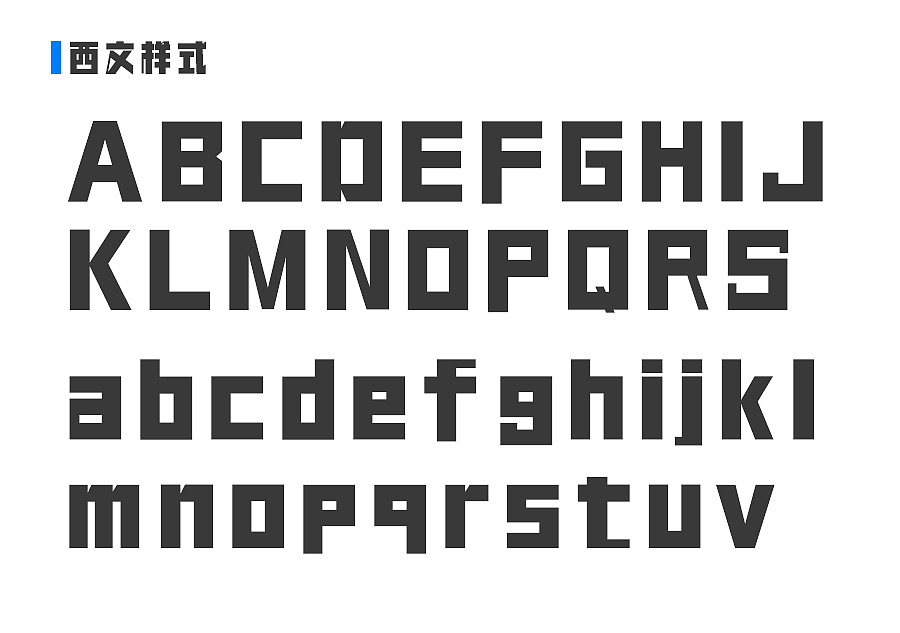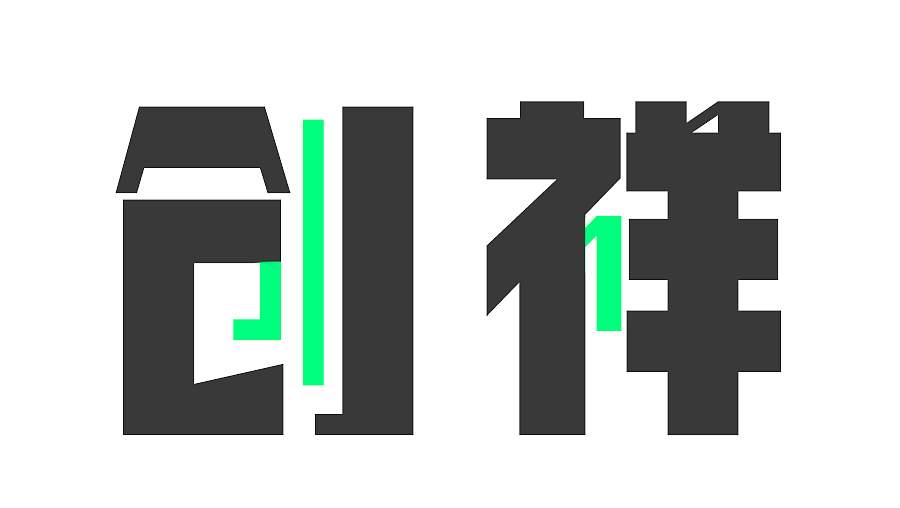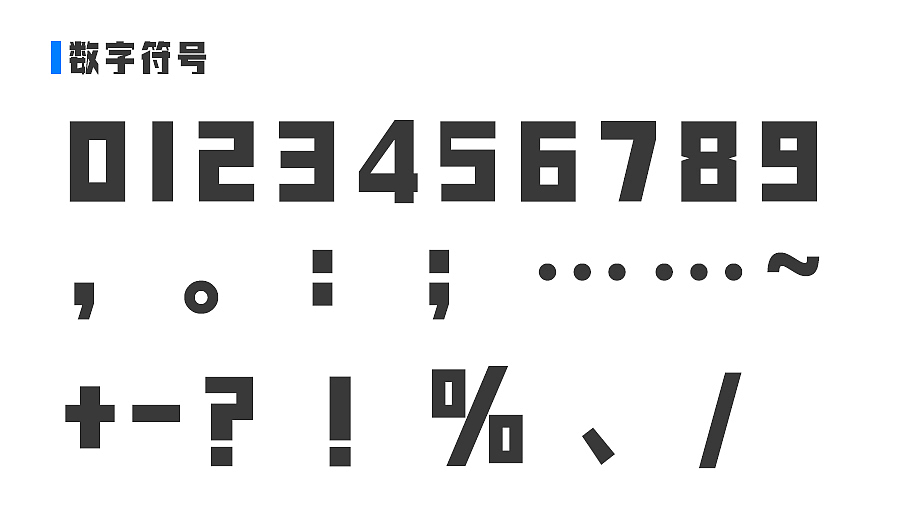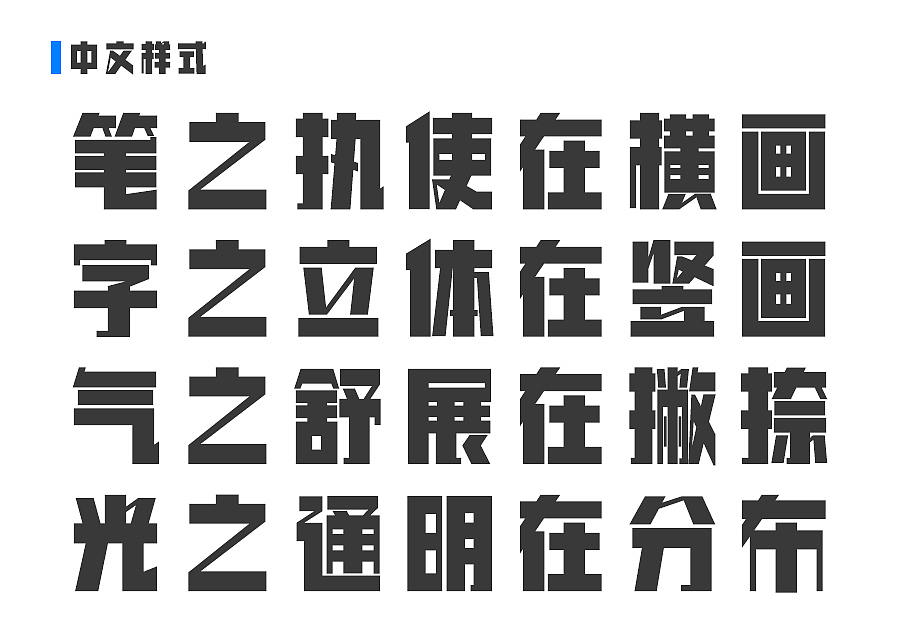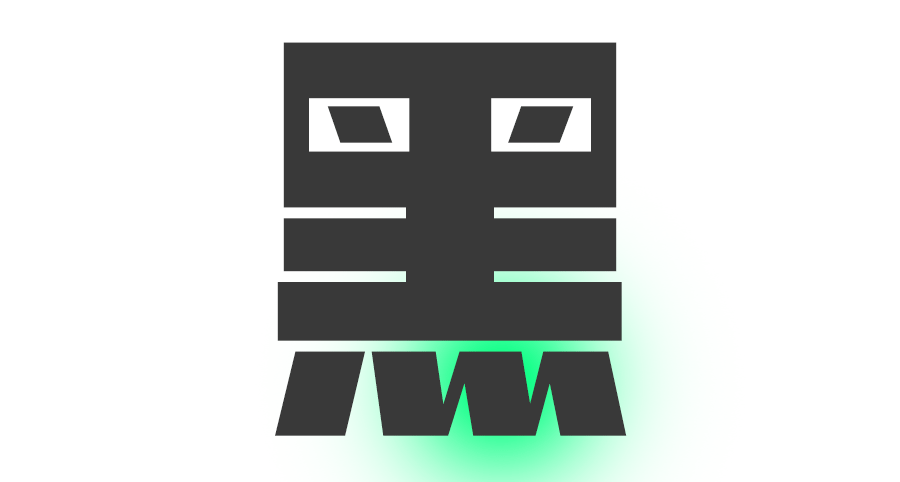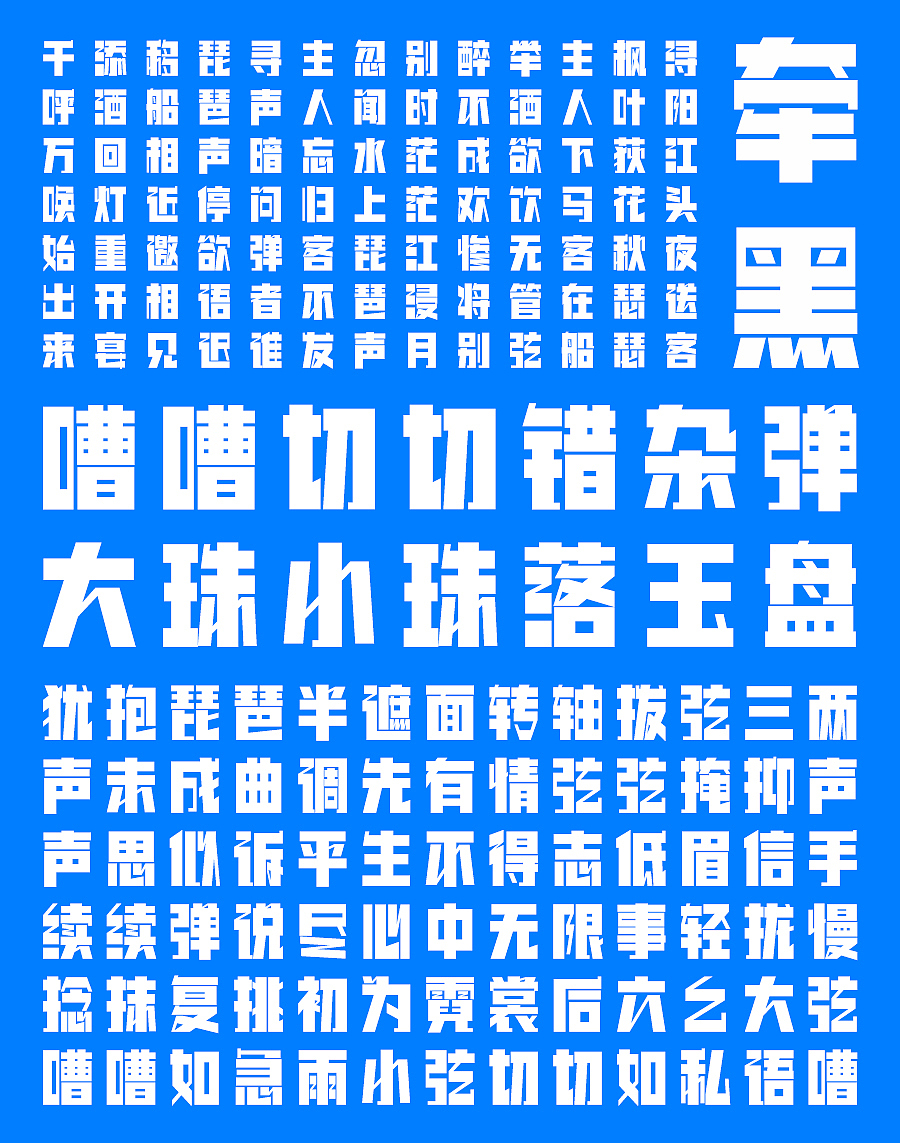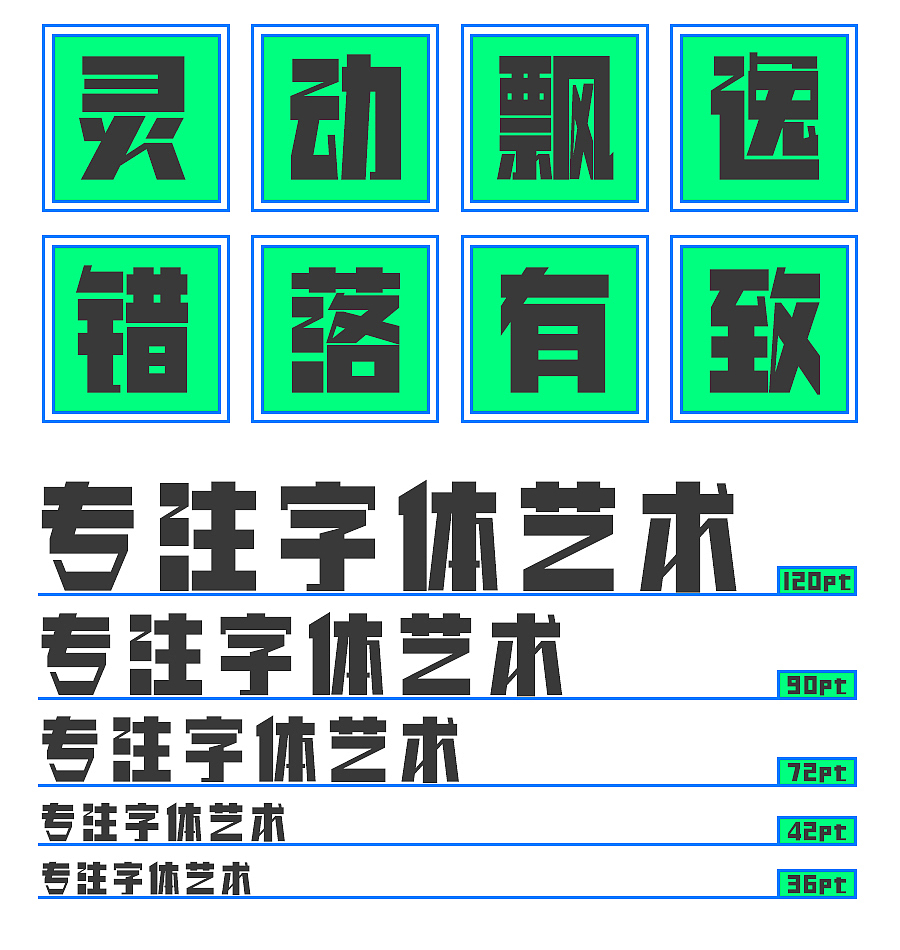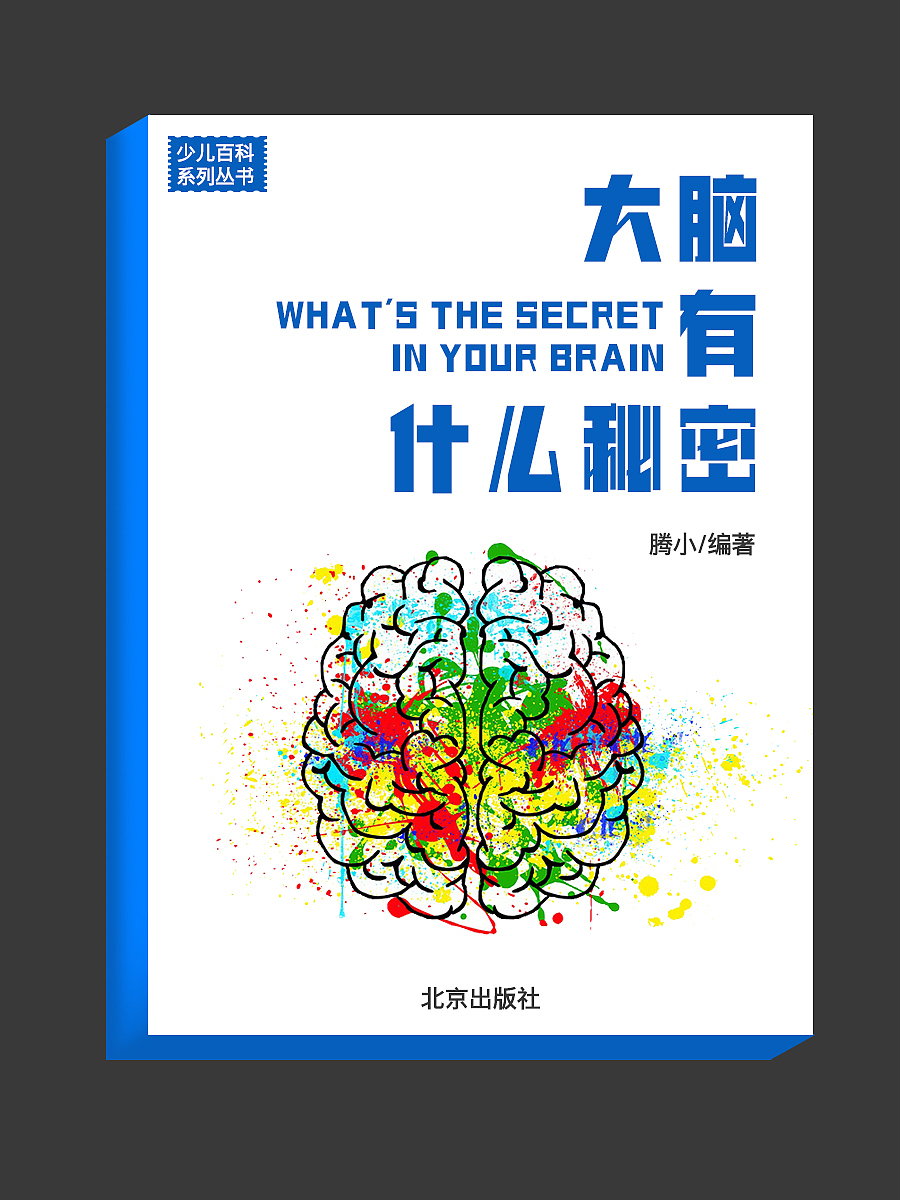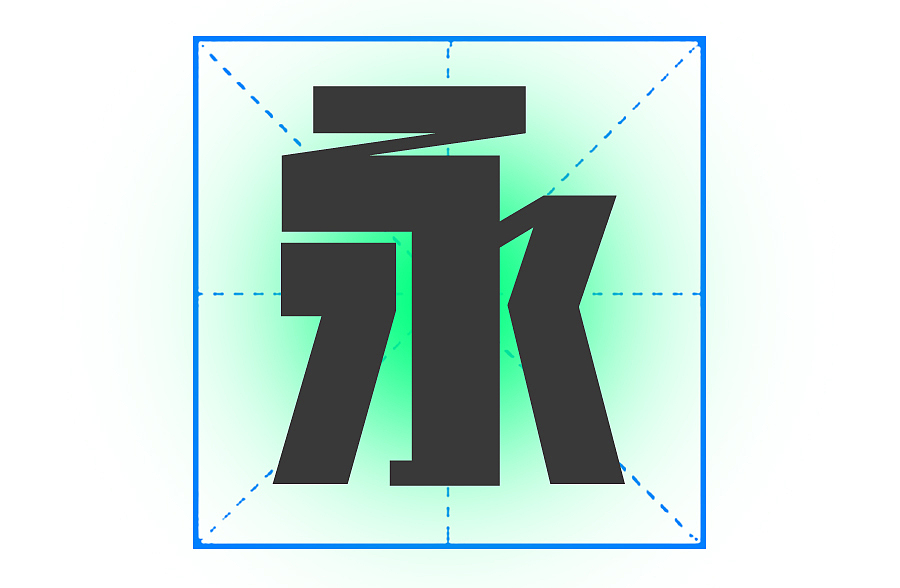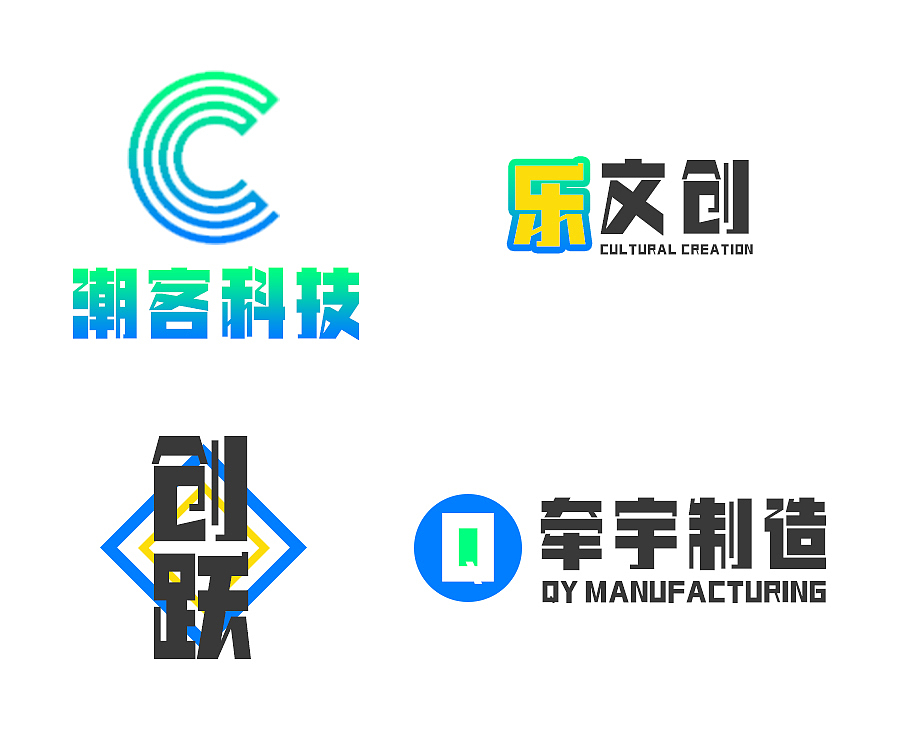
腾祥牵黑是腾祥公司自主精心设计开发的美术字体。牵黑体为黑体字形,其结构长方笔画粗壮醒目,其中细笔画穿插其中打破黑体字的沉闷,笔画粗细搭配协调,设计凝练巧妙,在不影响阅读的前提下牵黑体中特别设计了连笔笔画处理,使黑体字看起来灵动有手写感。整幅字给人以清朗醒目、别致新颖之感。设计师以独具匠心的设计手法诠释出牵黑体的别样风格。
*同一个部件搭配不同的偏旁或身旁有不同的粗细变化,遇粗则细,遇细则粗,使单字的空间布局清晰,易读。
*笔画设计灵感来源于手写笔意又借鉴了行书连笔的笔势,撇捺、撇点等笔画以牵丝相连,游丝萦绕,使厚重的黑体字富于灵动飘逸之感。
*笔画简洁,粗细穿插错落有致、风格和谐统一、布白和谐统一、整体感协调统一。
腾祥牵黑属于标题用字,适用于数字媒体、印刷出版、包装设计、儿童读物、广告设计、网页设计等。(建议:字号36P以上使用)